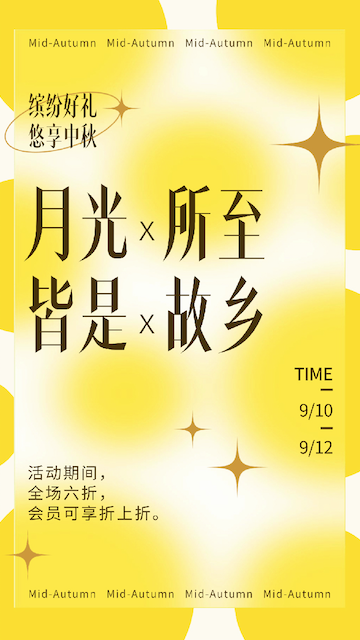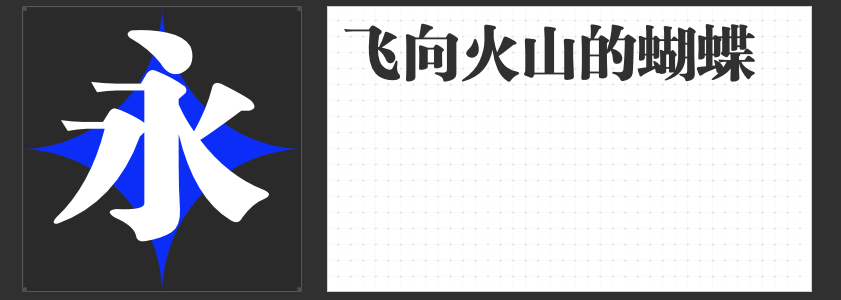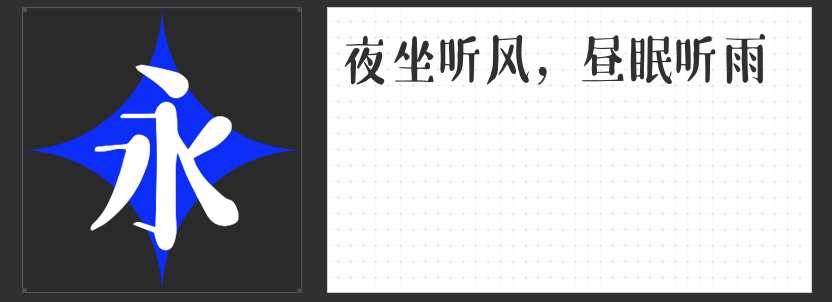
宋体字体的魅力:四款精选字体推荐
在汉字字体中,宋体字以其端庄、典雅的特点深受设计师和排版人员的喜爱。今天,将为大家推荐四款极具特色的宋体字体。这些字体不仅保留了宋体字的基本特征,还在细节上进行了创新,使得它们在不同场合下都能展现出独特的魅力。
首先,我们来看看“励字大标宋简繁”。这款字体结合了简体和繁体字的优点,使得它在满足不同地域和文化需求的同时,也能保持一致的视觉风格。其笔画粗壮有力,结构紧凑,非常适合用于标题和大型文字的排版,能够迅速吸引读者的注意力。
接下来是“高手庆科自由宋 常规”。这款字体在保持宋体字传统韵味的基础上,融入了更多的现代设计元素。它的笔画流畅自然,线条粗细适中,既不失古雅之感,又符合现代审美。无论是用于正文排版还是广告设计,都能展现出独特的艺术效果。
再来说说“高手兵克高雅宋”。这款字体以其高雅、精致的特点而著称。它的笔画细腻而有力,结构匀称而富有变化,能够很好地体现出宋体字的韵味和美感。无论是用于书籍封面还是高档宣传品的设计,都能彰显出作品的品质和价值。
最后是“励字新粗宋简”。这款字体以其粗犷、有力的特点而受到许多设计师的喜爱。它的笔画粗壮有力,线条明快,给人一种强烈的视觉冲击感。非常适合用于需要强调文字效果的场合,如海报、招贴画等。
综上所述,这四款宋体字体各具特色,能够满足不同场合下的设计需求。无论你是专业的设计师还是排版人员,都可以在这些字体中找到适合自己的那一款。希望这篇推荐文章能够帮助你更好地了解和选择宋体字体,为你的设计作品增添更多的魅力和价值。